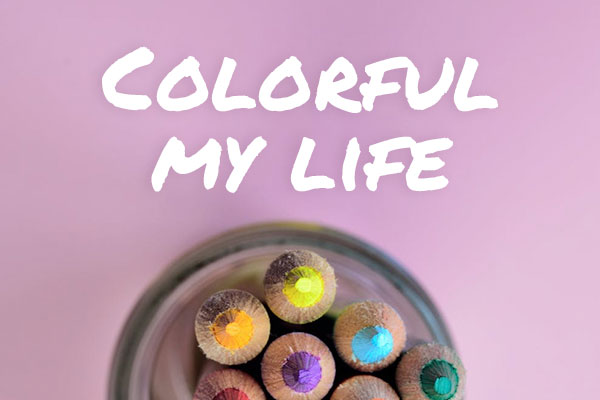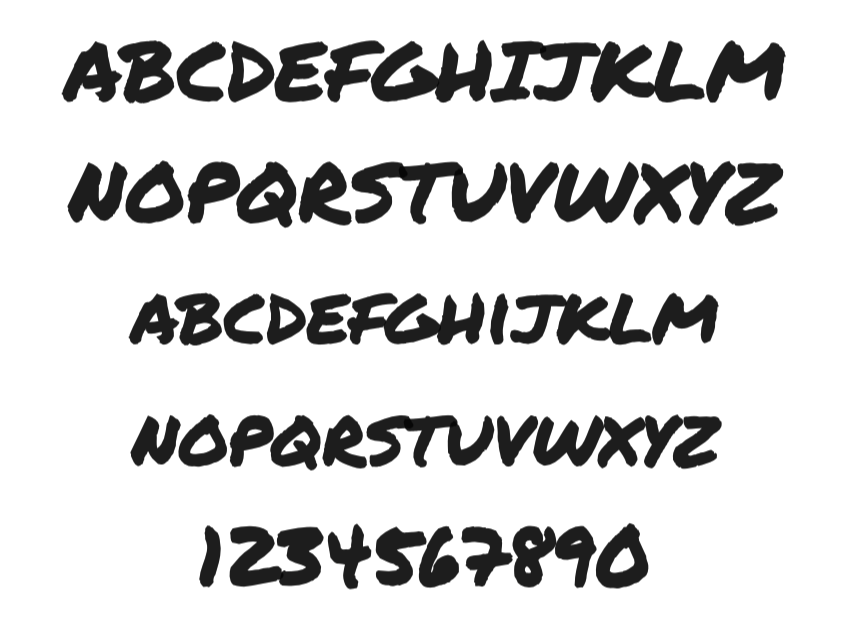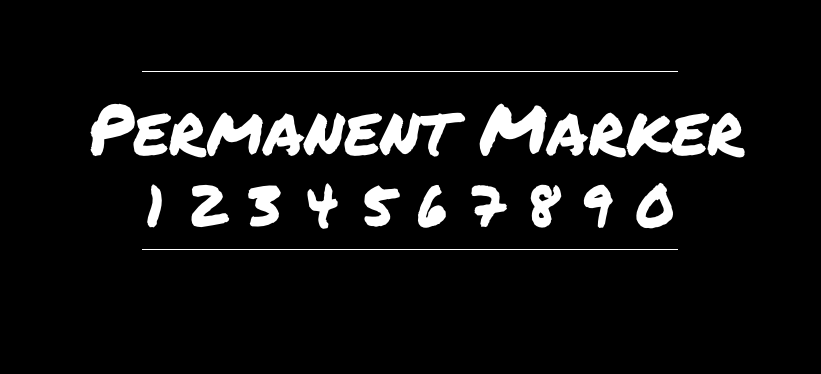
Permanent Marker
Permanent Marker字体介绍
Permanent Marker是Font Diner推出的一款英文字体,Permanent Marker是一款手写风格的字体,字形粗犷有力,可用于海报、LOGO等多种需要表现张力的场合。需要注意的是该字体小写字母也是大写的写法。Permanent Marker在GoogleFonts上开源发布,遵循Apache许可2.0版,您可以在产品和项目中自由使用它们,印刷或数字,商业或其他方式,但是您不能单独出售字体。
Permanent Marker字体应用示例